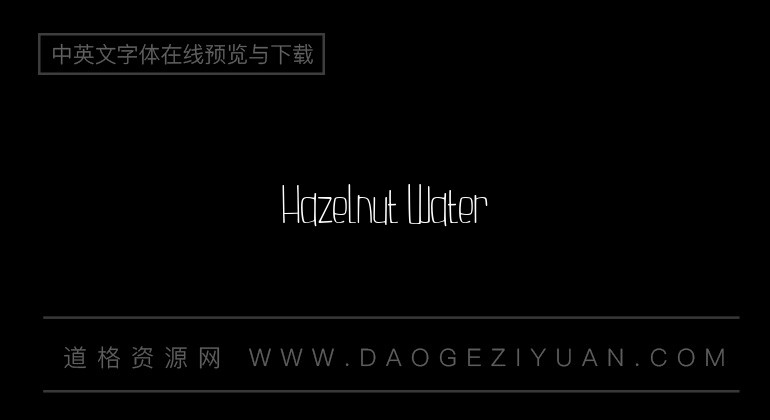
Hazelnut Water
Hazelnut Water是一种手写风格的字体,它的特点是非常自然、流畅、柔和,具有轻盈、温暖、亲切的感觉。这种字体的笔画比较细腻,弯曲的部分充满了动感,整体上非常适合用于文艺风格的设计,比如书籍封面、海报、手帐等。同时,Hazelnut Water字体也很适合用于各种印刷品,如明信片、贺卡、传单等。此外,由于它的可读性很高,因此也适合用于品牌标志和企业形象设计。
Hazelnut Water是一款非常不错的手写艺术字体,具有很好的视觉感,适合于文化类的宣传设计、商业类品牌的广告和产品包装设计以及个性化文字排版等较多场景。